¡Seguimos probando nuevos rotuladores de punta de pincel o de punta flexible! Ya sabéis que este tipo de rotuladores son perfectos para poder escribir caligrafía con pincel y, sobre esta base caligráfica, añadir efectos y decoraciones para convertirlo en hand-lettering o como inspiración o base para poder dibujar Brush Lettering, es decir, dibujar letras que parecen estar escritas con un pincel.
Características de los rotuladores acuarela de Faber Castell
Estas son las características más especiales de los Faber Castell Albrecht Durer Watercolor Markers:
- Punta doble, una redonda y otra de pincel flexible: la punta redonda permite hacer trazos regulares y la punta permite hacer trazos finos y trazos gruesos, lo cual es genial para caligrafía y lettering.
- Acuarelables: Como su nombre indica, son rotuladores de acuarela, por lo tanto, tienen tinta con base al agua y se pueden acuarelar para hacer degradados al añadirle agua y crerar unos efectos ideales en hand lettering.
- Alta pigmentación: A pesar de ser una tinta acuarelable, está altamente pigmentada para que los colores sigan siendo potentes y durables en el tiempo, siendo resistentes a la luz.
- Gama amplia de colores: Se pueden encontrar en 30 colores distintos.
Relación Calidad – Precio de los rotuladores acuarela de Faber Castell
Prueba de los rotuladores acuarela de Faber Castell
Ahora es el momento de que os enseñe las pruebas que he realizado con estos rotuladores de acuarela Albrecht Durer Watercolor Markers.
Efecto acuarela
Así se comportan estos rotuladores de acuarela cuando le añades agua con un pincel con depósito del agua sobre un papel del cuaderno Winsor & Newton Drawing & Sketching Paper. Es un acuarelado es bastante fluido y agradable, mantienen el color vivo.
Al secarse, el resultado es este, aunque puede cambiar mucho dependiendo de la cantidad de agua y del papel utilizado:
Me gusta el resultado, tiene matices muy interesantes y naturales, con texturas muy artísticas.
Trazos finos y gruesos para caligrafía y lettering
En lo que nos concierne, también los he probado para caligrafía y lettering. Me gusta cómo realiza los trazos finos y gruesos, además, el pincel hace una especie de degradado natural de izquierda a derecha por la acumulación de pinta en la parte inferior.
Degradado para hand lettering
También quise probar cómo funcionan para degradado en hand lettering, en este caso, de azul a negro, y este es el proceso:
El resultado en seco es bastante similar, muy lleno de matices. Echadle un vistazo al vídeo que hay al final de este artículo para ver todo el proceso.
Cómo quedan sobre distintos papeles
Si hay algo que me gusta de estos rotuladores es su resultado sobre papel satinado o papel couché:
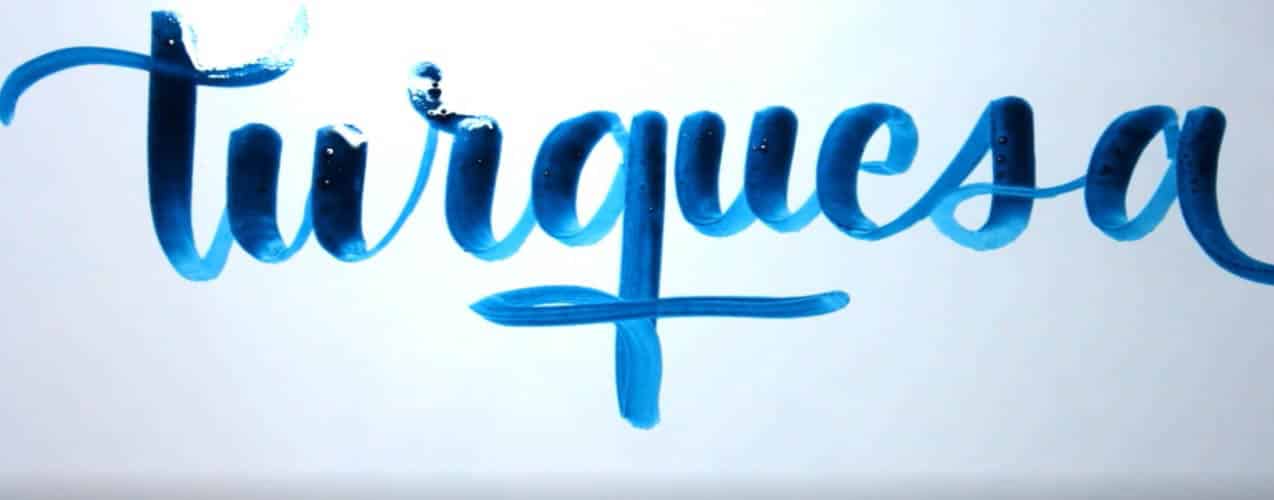
Se deslizan de maravilla y quedan unos reflejos alucinantes. ¡Fijaos en los reflejos dorados naturales que salen en el color Pink Carmine!
Vídeo reseña rotuladores acuarela de Faber Castell
Si no queréis perderos ni un detalle sobre estos rotuladores y todo lo que os he mostrado, os recomiendo que echéis un vistazo al vídeo de mi canal de Youtube Azahara Letras, en donde podéis ver todo paso a paso y con más pruebas aún:
Conclusión
En definitiva, estos rotuladores de acuarela Faber Castell Albrecht Durer Watercolor Markers son buenos y merece la pena invertir casi 4 € en ellos. No solo sirven para caligrafía y lettering, sino que también los podrás usar si dibujas con acuarelas. Lo que más me gusta de ellos es la potencia de su color y sus degradados naturales, así como sus reflejos sobre papel couché.